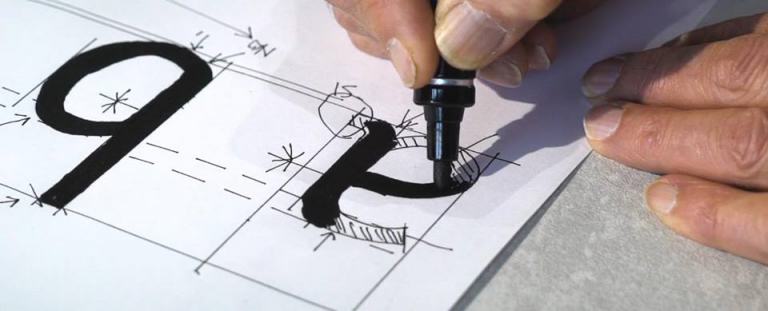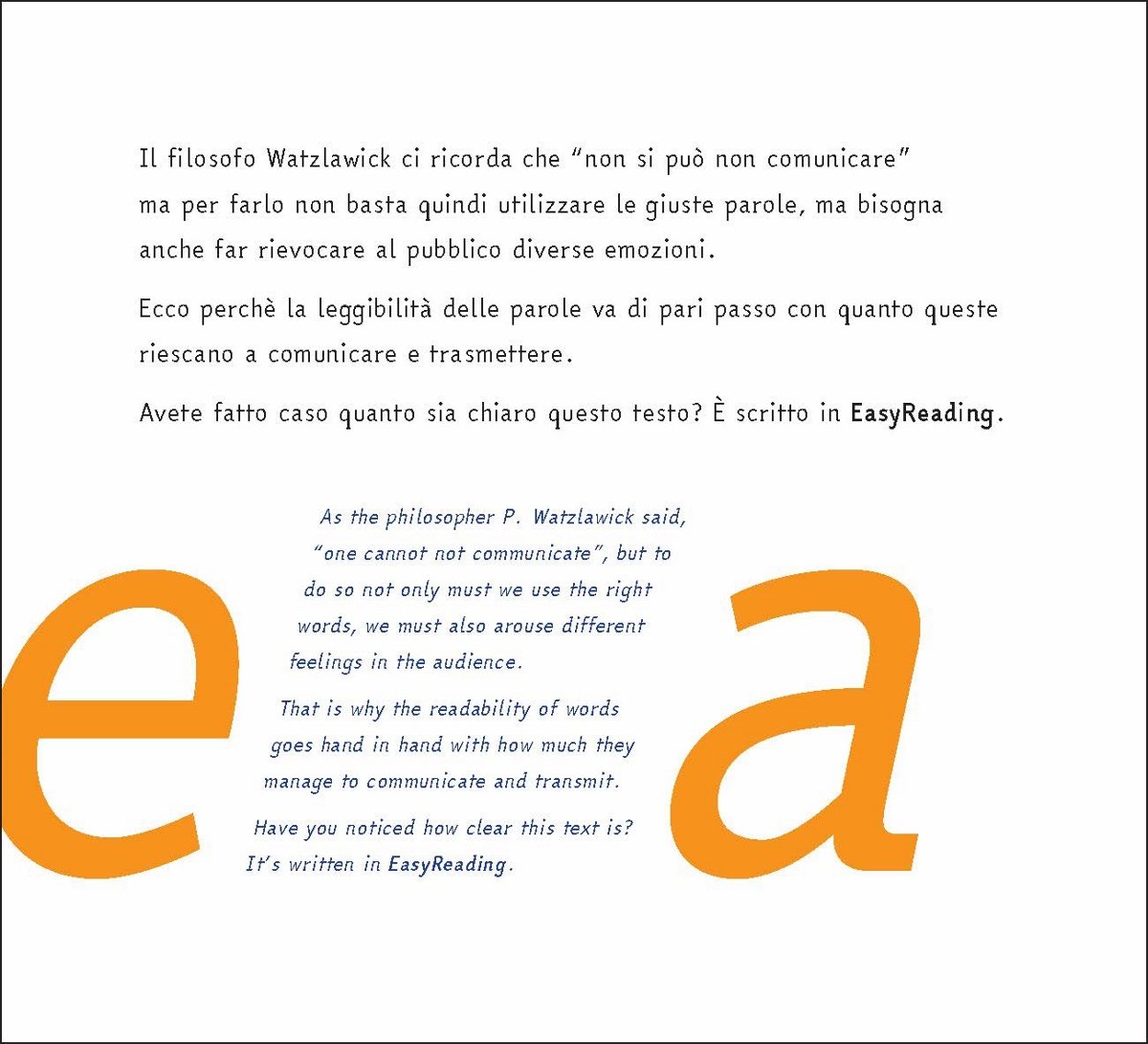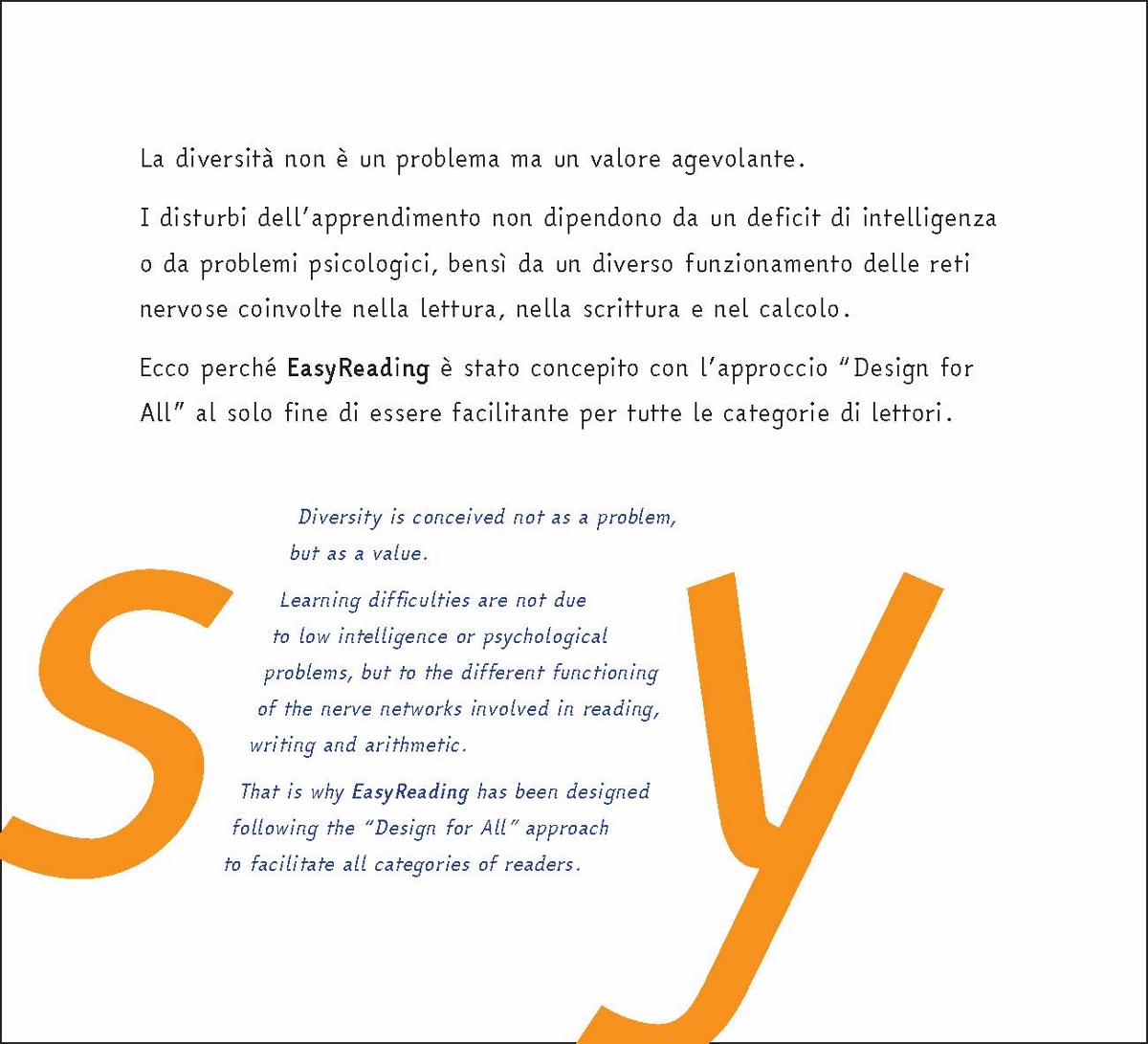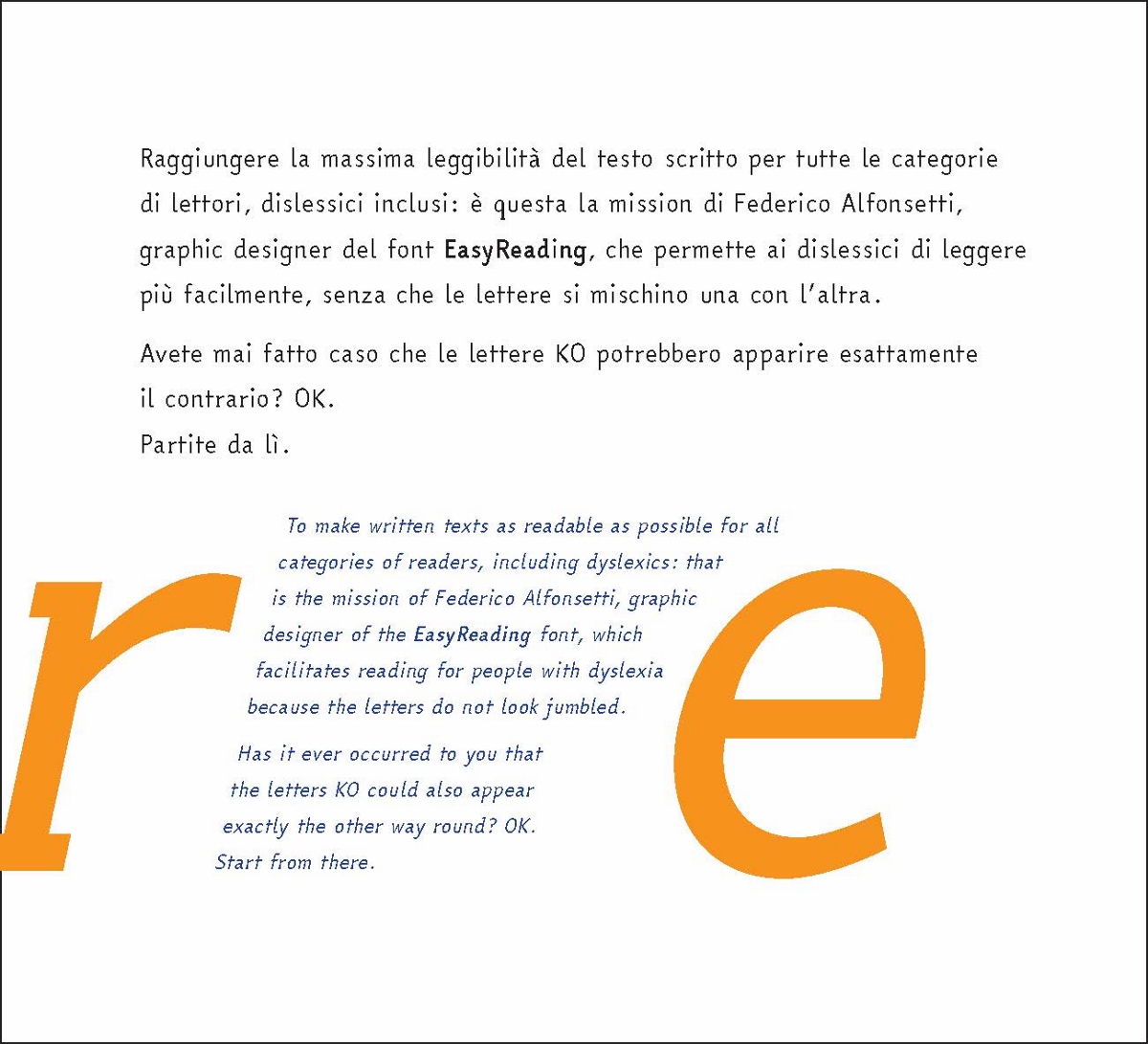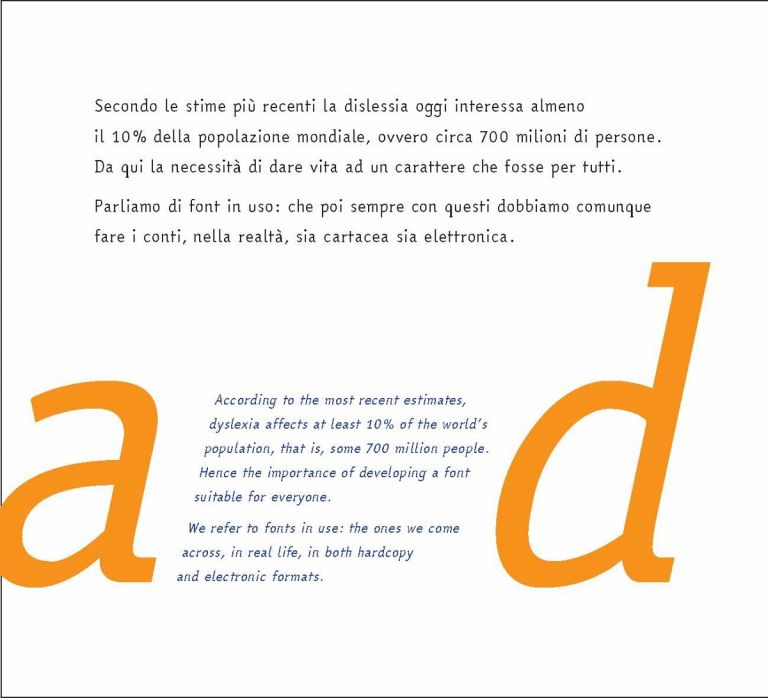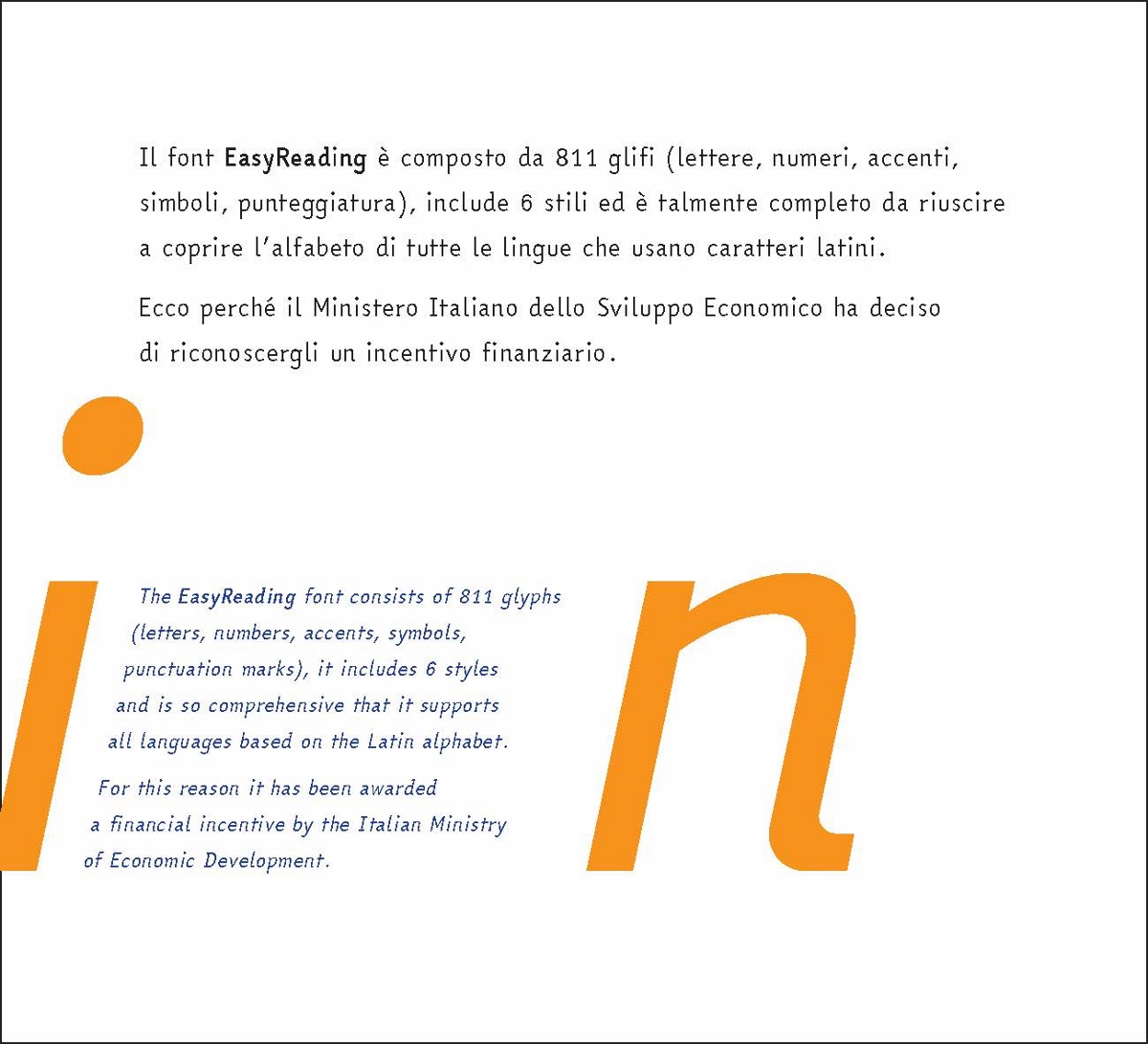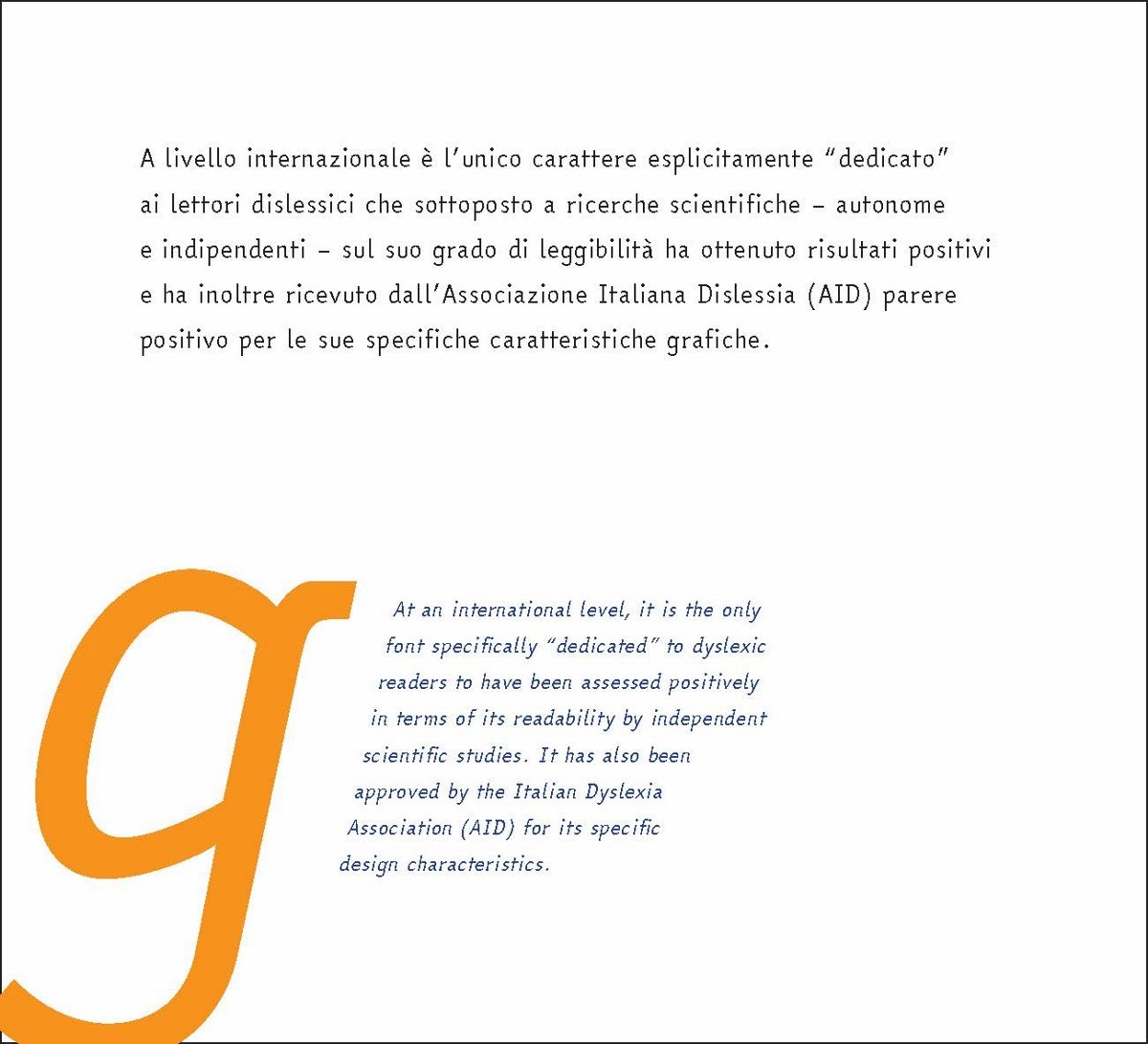
Design for all e Intelligenza Artificiale. Primo font per dislessici all’Università della Tuscia
L’Università degli Studi della Tuscia ha adottato il font EasyReading, creato a Torino dal designer Federico Alfonsetti per chi soffre di dislessia, anche per il progetto europeo VRAIlexia che usa l’AI per migliorare l’apprendimento dei suoi studenti
Una storia di design e di un font ad alta leggibilità pensato per i dislessici: EasyReading creato a Torino dal designer Federico Alfonsetti. È quella che vi abbiamo raccontato qualche anno fa qui su Artribune e che ora torna sotto i riflettori grazie alla scelta dell’Università della Tuscia di utilizzare questo carattere tipografico – realizzato secondo l’approccio inclusivo del “Design for all” – anche per il progetto europeo VRAIlexia, una piattaforma di e-learning che fa uso dell’Intelligenza Artificiale per migliorare l’apprendimento dei suoi studenti. Il termine è un acronimo che condensa tutte le sfaccettature del progetto: VR sta per realtà virtuale, AI per l’intelligenza artificiale, mentre lexia rimanda agli strumenti basati su cloud e su intelligenza artificiale in grado di interagire con l’uomo.
EasyReading
EASYREADING: LA GENESI DEL PROGETTO
“L’idea è stata del professore di Ingegneria dell’Università degli Studi della Tuscia Giuseppe Calabrò il quale, aveva già presentato al Ministero Tua2 un progetto di Ricerca e Formazione a livello nazionale. L’obiettivo è quello di far diventare l’ateneo un laboratorio permanente di ricerca, sperimentazione e didattica innovativa”, ha detto la project manager Marcella Barone. “A settembre 2019 abbiamo pensato di sviluppare l’idea a livello europeo e grazie ad una progettazione partecipata, abbiamo presentato la proposta in risposta al bando Erasmus + del 2020. Grazie all’interdisciplinarietà del team che ha preso parte alla stesura del progetto e al carattere fortemente innovativo della proposta, il progetto è risultato il primo in graduatoria e dal primo settembre 2020 abbiamo iniziato ufficialmente con le attività”.
Federico Alfonsetti, il designer
EASYREADING: COME FUNZIONA
Un progetto che è stato tra i primi a trattare un tema tanto delicato come quello della dislessia nell’apprendimento. Così, dopo aver acquisito la licenza d’uso del font ad alta leggibilità EasyReading® Dyslexia Friendly su tutti i PC dell’ateneo e come predefinito per le attività didattiche telematiche, l’Università degli Studi della Tuscia ha scelto di utilizzare il font anche per il progetto europeo VRAIlexia. “Siamo felicissimi di poter portare avanti questa partnership, con l’utilizzo del nostro font in tutti gli strumenti pensati e creati ad hoc nel progetto”, ha dichiarato il designer del font e amministratore delegato della società Federico Alfonsetti. “È stata la prima università, in Italia, a credere nell’importanza dell’utilizzo di un font ad alta leggibilità e si è confermata visionaria in questo frangente, nel quale può fare da apripista perché altre realtà analoghe si muovano nella stessa direzione”. Il font disegnato a Torino da Federico Alfonsetti e dal suo team di ricerca ha come target il 10% della popolazione che soffre di dislessia, ma ha punta anche alla semplicità e all’alta leggibilità per tutti: il design dei suoi 811 caratteri agevola i lettori dislessici ma è del tutto leggibile anche per il lettore comune, che con ogni probabilità non si renderà conto di trovarsi di fronte a un carattere “speciale”. Per questo la sua applicazione è possibile in molteplici campi, dall’editoria ai musei, e ora anche all’Università. “L’Università degli Studi della Tuscia è un Ateneo giovane a misura di studente,” ha concluso Giuseppe Calabrò, Responsabile scientifico progetto VRAIlexia, “il nostro Rettore punta a far diventare l’Ateneo un centro nevralgico per la realizzazione degli Obiettivi di Sviluppo Sostenibile dove ogni studente trova le condizioni per esprimere al meglio il proprio potenziale. È in questa ottica che abbiamo deciso di adottare il font ad alta leggibilità EasyReading e di intraprendere iniziative come VRAILEXIA dove in maniera innovativa vogliamo rompere gli schemi ed essere promotori di una rete di Campus Sostenibili”.